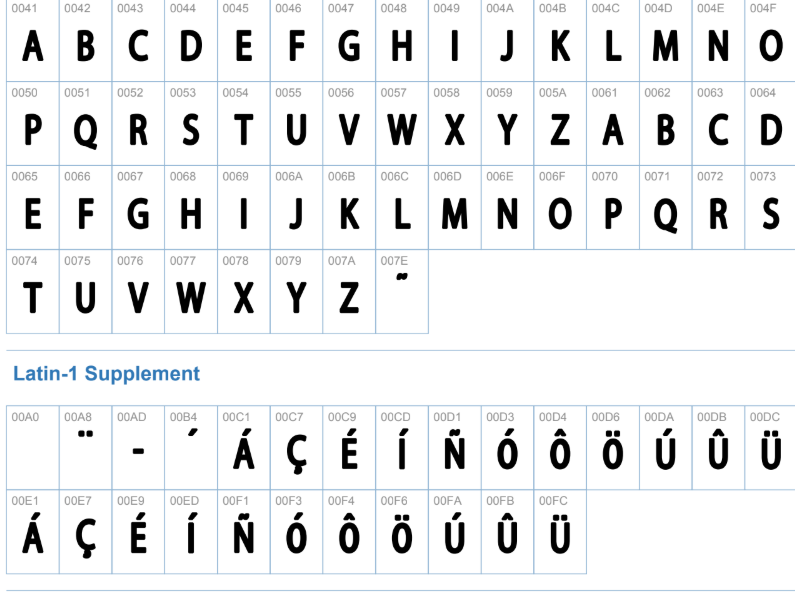
A paixão pelo Santos FC vai muito além dos 90 minutos. Ela está na história, nos ídolos e, claro, no “Manto Sagrado”. Na temporada 2025, a Umbro caprichou mais uma vez, entregando uniformes que honram a tradição do Peixe, e um detalhe crucial dessa identidade é a tipografia (fonte) usada nos números e nomes dos jogadores.
• Nome: Santos FC 2025 (Tipografia oficial Umbro)
Análise do Estilo Visual
A tipografia do Santos FC para 2025 combina modernidade com legibilidade. Ela possui cantos sutilmente arredondados e uma estrutura robusta, garantindo que os números e nomes sejam perfeitamente visíveis de longe, tanto na transmissão da TV quanto das arquibancadas da Vila Belmiro.
É uma fonte sem serifa (sans-serif) limpa, que transmite velocidade e seriedade, alinhada à identidade visual que a Umbro tem construído para o Alvinegro Praiano. Ela é usada em todos os uniformes oficiais da temporada: o tradicional branco, o listrado (branco e preto) e os uniformes alternativos ou de goleiro.